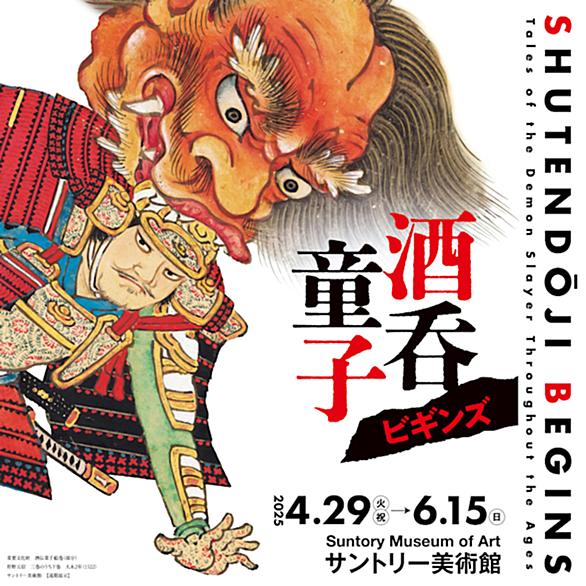
◯酒呑童子ビギンズ#にみるクールジャパン これを今更、かこつけるのも変ですが、その後の文化、さらに、日本の漫画、アニメにも、ストレートに影響しています。 ここに映画のように、ビギンズと名づけんのか。 漫画の代表といえば、鳥獣戯画#もこの美術館で見たことがあります。文化放送の引地副館長から招かれ、ネスドルチェのコーヒーをご馳走になったことも。18年も前らしい、、、。 今回も絵を見に行ったのですが、加えて、かな文字、その書体の美しいことが、特に印象に残りました。私の親の世代くらいまでは、女性には、美しいくずし字、連綿体、草書体で手紙を書く人もいたのですが、これも失われていく文化の一つなのでしょう。…